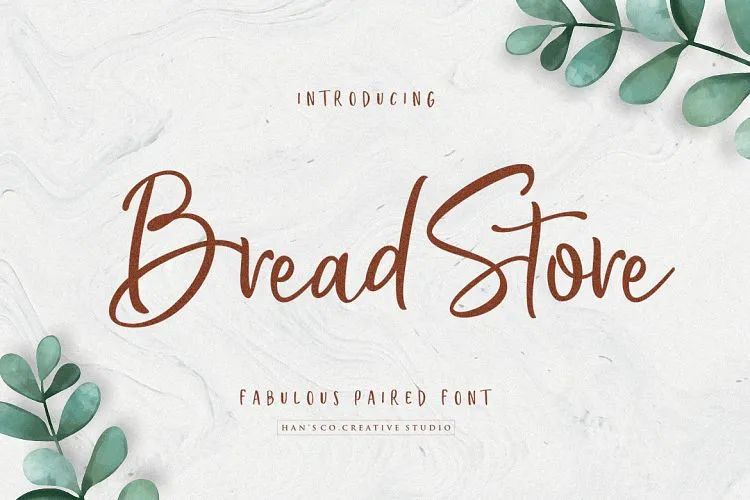
Bread Store Script Font – Fonte Grátis
Bread Store Script Font
Bom dia! Na categoria de Fontes Script, apresentamos a Bread Store Font, criada pelo designer Hamilton. Esta é uma tipografia moderna e elegante, com traços finos e femininos, que mantém um tom amigável. Inspirada no estilo da loja de pão, esta fonte representa o rústico em linhas modernas. Suavemente feminina e versátil, a Bread Store Font é uma excelente escolha para criar logotipos elegantes, embalagens ou cartões de convite. Ela também se destaca quando usada sozinha, como background para frases escritas à mão ou como fonte de citações. Esta fonte é perfeita para quem busca um estilo simples e moderno que transmita serenidade e elegância. Não perca essa oportunidade de tornar seus materiais design mais sofisticados e distintivos. Baixe a Bread Store Font hoje!